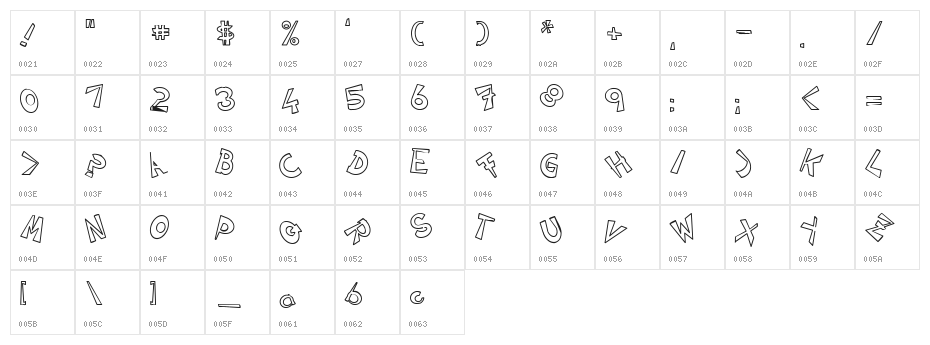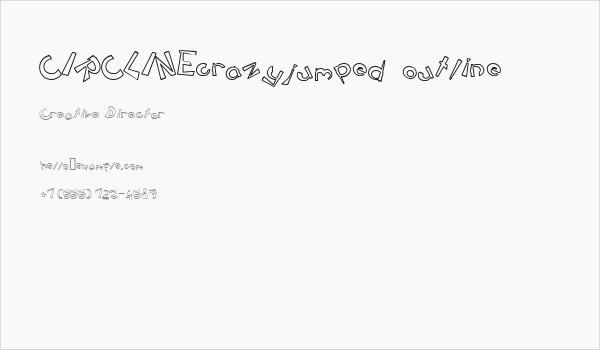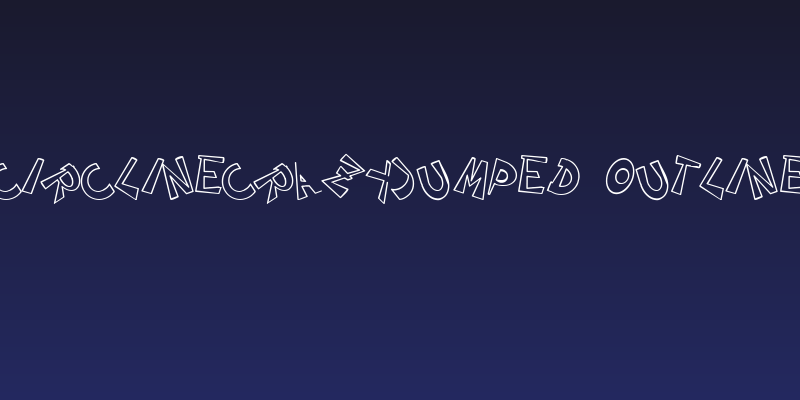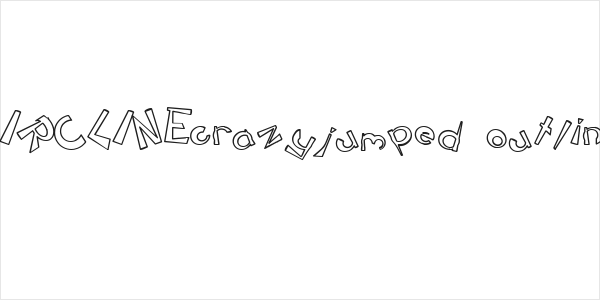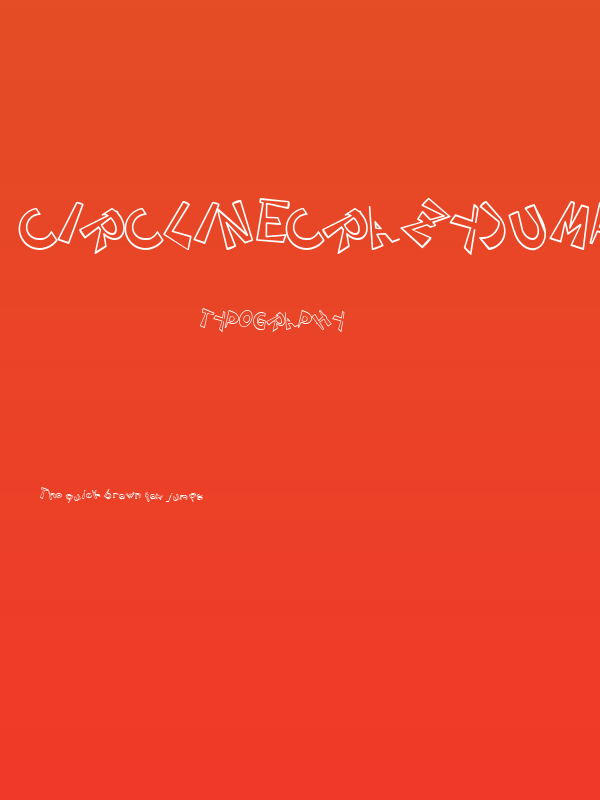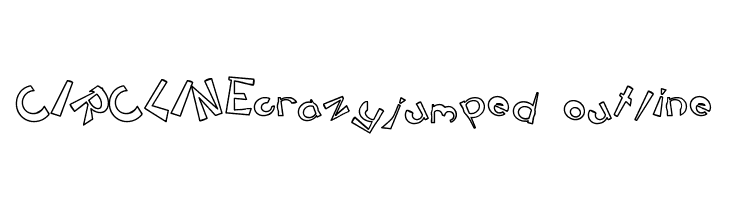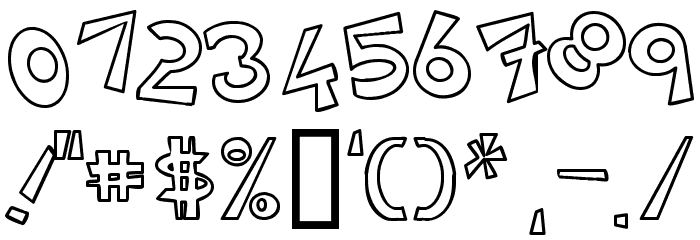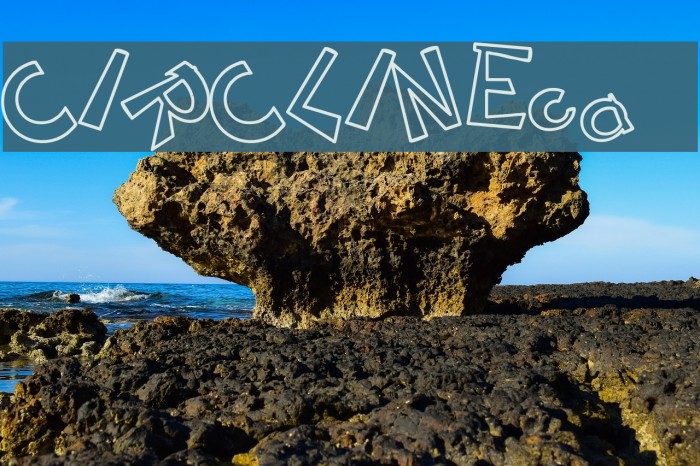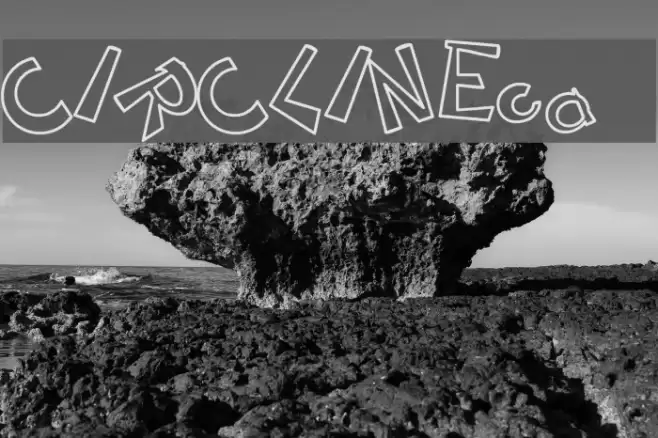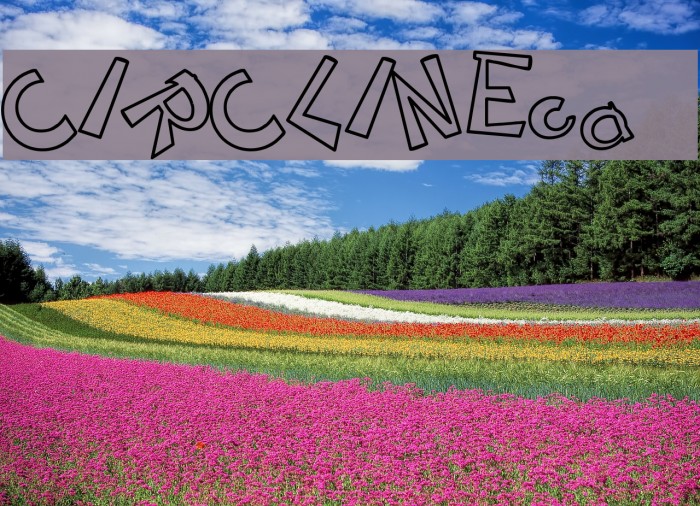
CIRCLINEcrazyjumped outline Font
✎ Outline
| Gesamtstil | Playful, Whimsical |
| Vorgeschlagene Projekte | Ideal for children's book covers, playful branding, creative posters, and fun social media graphics. |